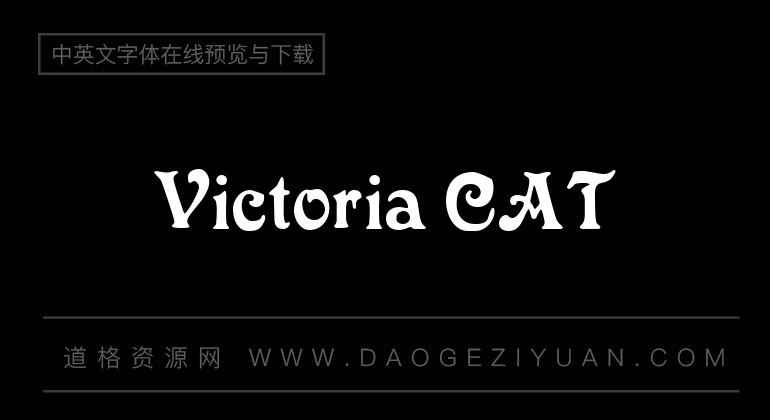
? Victoria CAT 是一款精美的英文字体,它有着流畅的笔画和清晰的结构,可以带来清新的视觉效果。Victoria CAT 的特点是它的笔画细腻,让文字变得更加精致和细腻,而且它的字体重量也比较轻,可以使文字显得更加精细。它也适用于多种设计场景,可以用于商业广告、海报、海报等,也可以用于书籍封面、报纸标题、网页等等。内容介绍
Victoria CAT是一款非常不错的手写艺术字体,具有很好的视觉感,适合于文化类的宣传设计、商业类品牌的广告和产品包装设计以及个性化文字排版等较多场景。